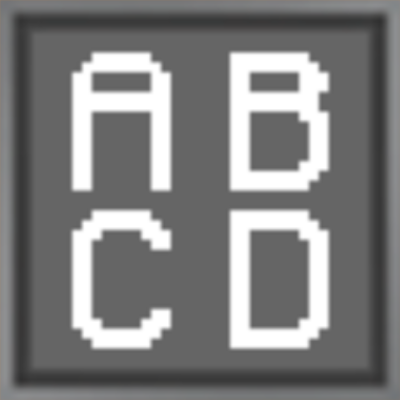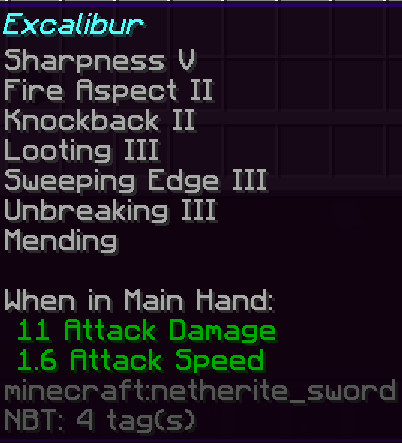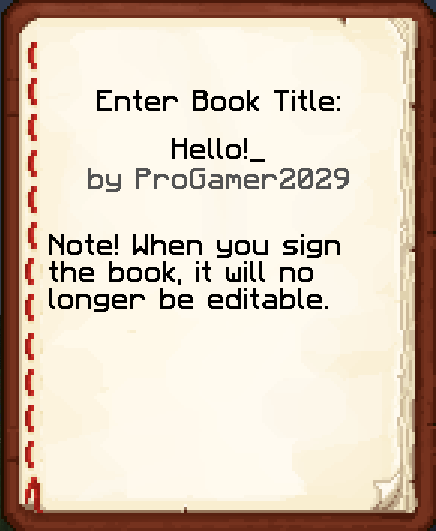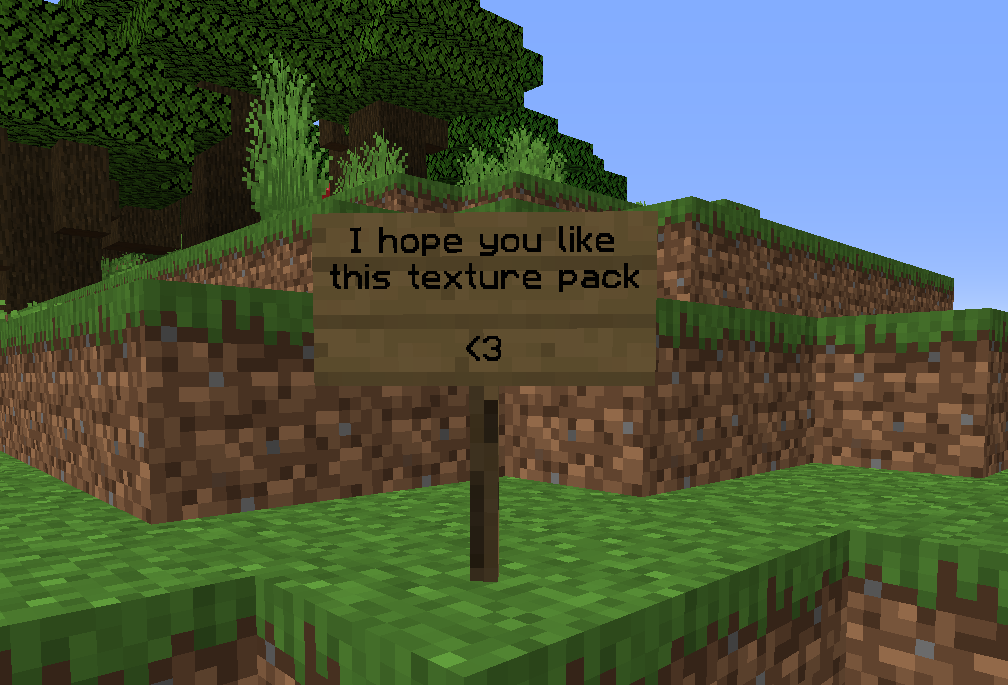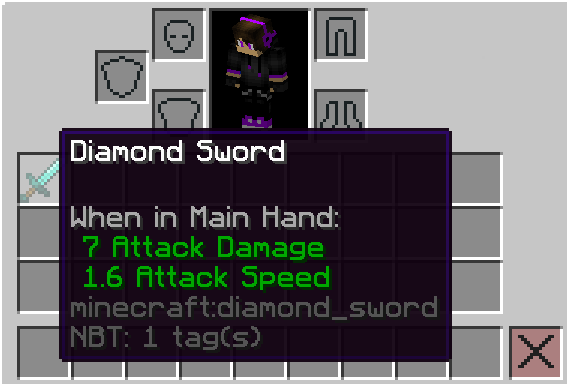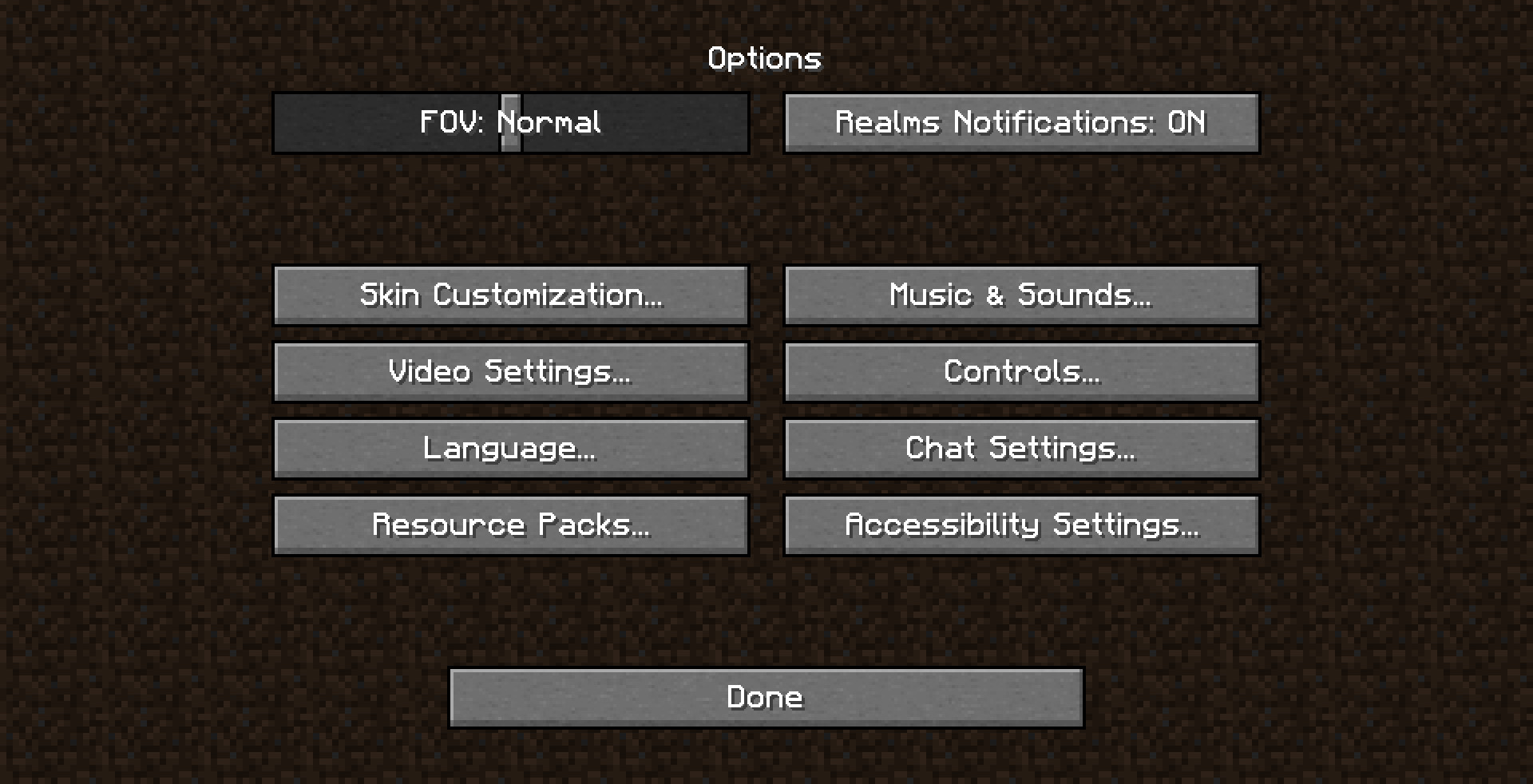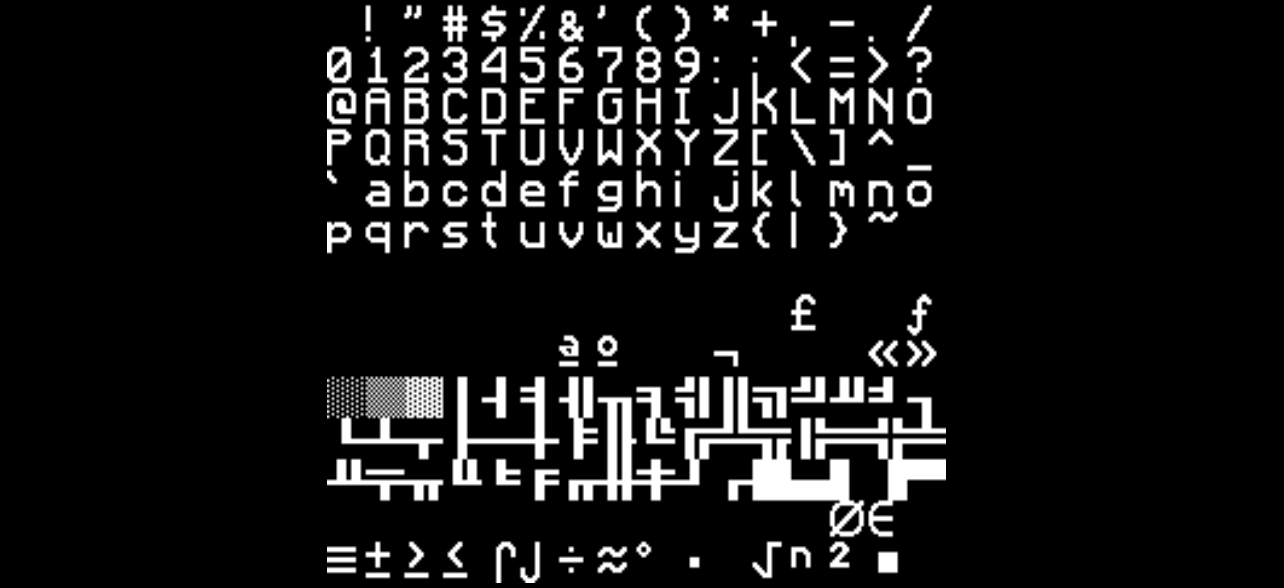
Minecraft Font Fix — исправляем странный шрифт в игре
Если вы замечали, что шрифт в Minecraft выглядит нечётко или странно, вы не одиноки! Многие игроки сталкиваются с этой проблемой, особенно при использовании HD-текстур или модов. В этой статье разберём, как исправить шрифт с помощью специального текстура и улучшить читаемость текста в игре.
🔍 Почему шрифт в Minecraft выглядит странно?
Проблема может возникать по нескольким причинам:
- Низкое разрешение стандартного шрифта — в оригинальной игре он рассчитан на 16x пикселей.
- Конфликт с модами — некоторые аддоны изменяют интерфейс, что влияет на отображение текста.
- Использование текстурпаков — HD-ресурспаки (например, 32x или 64x) могут делать шрифт размытым.
🎨 Текстурпак для исправления шрифта
Один из лучших вариантов — Font Fix Texture Pack, основанный на популярном Faithful 32x. Он меняет только шрифты (буквы, цифры, символы), оставляя остальные текстуры без изменений.
🔹 Особенности пакета:
✔ Чёткий и удобочитаемый шрифт — улучшенная детализация.
🛠️ Дополнительные советы по улучшению шрифта
Если проблема сохраняется, попробуйте:
- Использовать OptiFine — этот мод оптимизирует графику и улучшает отображение текста.
- Проверить настройки шейдеров — некоторые эффекты могут влиять на чёткость шрифтов.
🏁 Заключение
Странный или размытый шрифт в Minecraft — распространённая проблема, но её легко исправить с помощью специального текстурпака. Font Fix Texture Pack — отличное решение для тех, кто хочет сделать текст в игре более читаемым без изменения остальных элементов. Попробуйте его, и ваши глаза скажут вам спасибо!